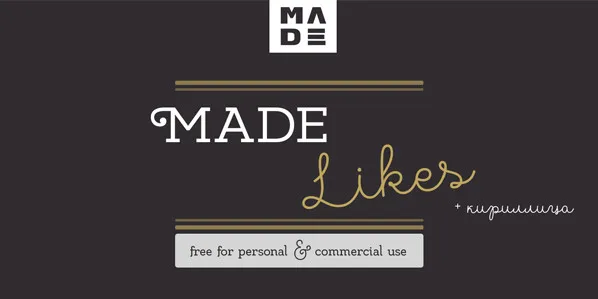
MADE Likes Font Family – Download Grátis
A MADE Likes Font Family é uma elegante família de fontes retro que combina elementos futuristas com linhas vintage perfeitas para criar designs inovadores e memoráveis. Este conjunto de fontes, disponível gratuitamente tanto para uso pessoal quanto comercial, oferece um toque distinto aos seus projetos digitais ou impressos. Sujeitada à categoria Retro Fonts, a MADE Likes Font Family é o resultado da colaboração entre criatividade e inspiração do século passado. Sua família de fontes inclui variadas opções para títulos e corpo que garantem uma experiência visual agradável e versátil. O designer MADE Type criou esta famosa fonte com um cuidado refinado, garantindo uma variedade suficiente de características que vão desde os detalhes mais sutis até as formas mais robustas. Esta fonte é ideal para aqueles buscando um design único e contemporâneo sem abrir mão do charme e dos traços clássicos. Sempre atento à qualidade e aos detalhes, o designer certificou essa fonte como de uso livre tanto em seu uso pessoal quanto comercial, garantindo que todos possam ter acesso a esta arte digital encantadora. Com uma gama de opções para personalizar sua marca ou projeto, a MADE Likes Font Family se torna um elemento chave no arsenal de designers digitais e fãs da cultura do design. Sempre procurando por mais e melhores maneiras de criar e inspirar novas ideias, esta fonte é uma excelente adição à sua coleção de ferramentas criativas.